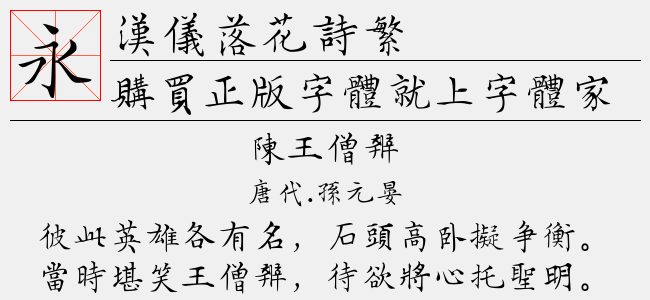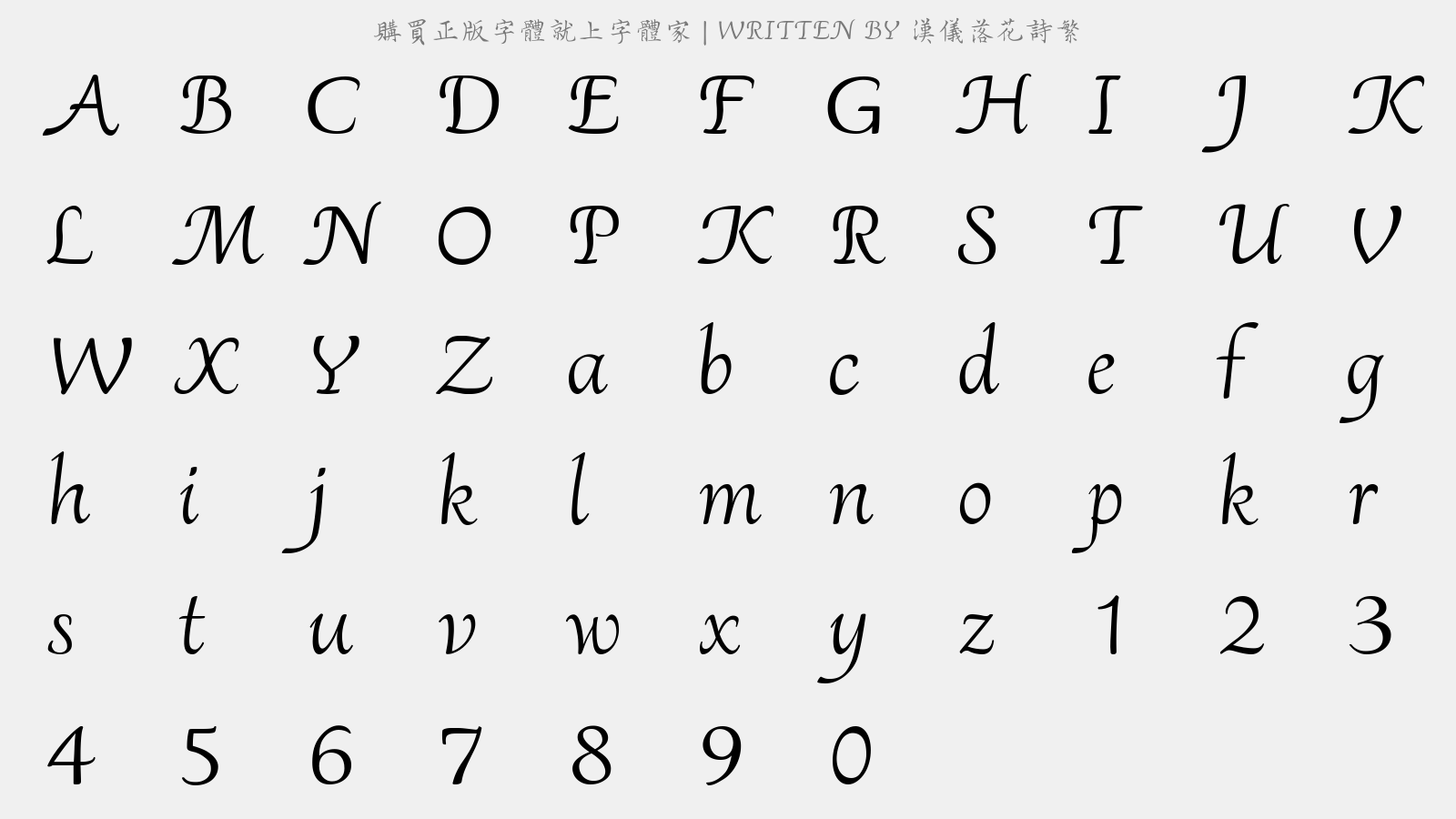
汉仪落花诗繁
字体作者:汉仪字库
字体名称:汉仪落花诗繁
字体字数:6763个汉字及26个英文大小写字母
书体类型:书法字库类
汉仪落花诗繁是由汉仪字库出品的一款中文字体,是一款似花唯美的字体,字体整体线条纤细,落笔柔软,刚劲之中又带有一丝丝文艺的气息。
汉仪落花诗繁 - 预览1
汉仪落花诗繁 - 预览2
汉仪落花诗繁 - 预览3
汉仪落花诗繁 - 预览4
汉仪落花诗繁 - 预览5
汉仪落花诗繁 - 预览6
汉仪落花诗繁 - 预览7
汉仪落花诗繁 - 预览8
汉仪落花诗繁 - 预览9
汉仪落花诗繁 - 预览10
汉仪落花诗繁 - 预览13
汉仪落花诗繁 - 预览18
汉仪落花诗繁 - 阮郎归(海岱楼与客酌别作)
汉仪落花诗繁 - 听赵秀才弹琴
汉仪落花诗繁 - 度清霄(其四)
汉仪落花诗繁 - 大写字母/小写字母/数字